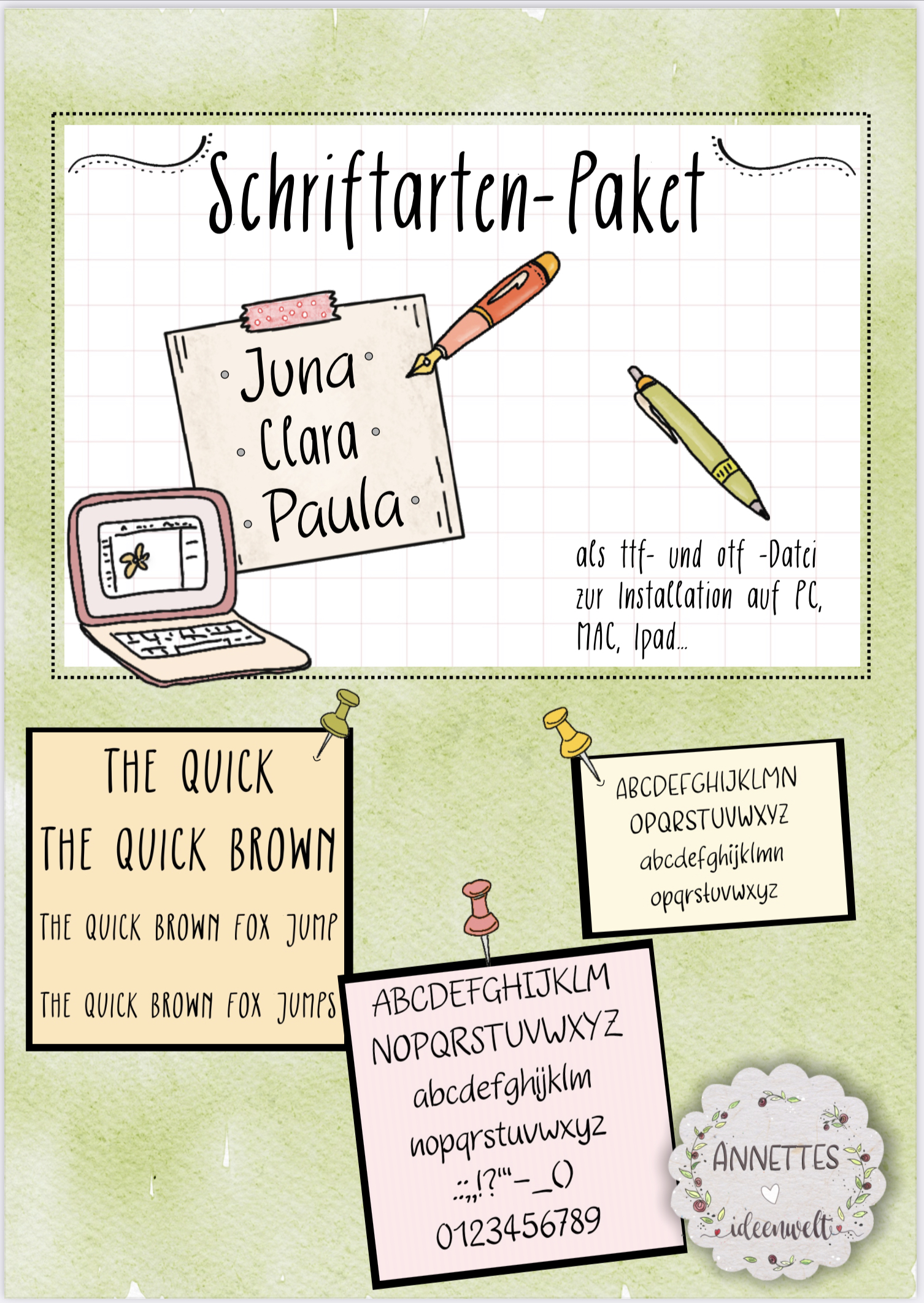
Drei klare, schlichte selbst erstellte Schriftarten, die sich hervorragend eignen um Arbeitsblätter oder sonstiges Material für die Schule herzustellen.
Schriftarten / Font Paket
Schriftart / Font "Clara"
Klare und schlichte Schriftart zum Erstellen von Arbeitsblättern und anderem Unterrichtsmaterial.Die Schriftart kann einfach installiert und in unterschiedlichen Programmen und Apps ( Windows/MAC/Ipad...) genutzt werden.
Schriftart / Font "Juna"
Klare und schlichte Schriftart zum Erstellen von Arbeitsblättern und anderem Unterrichtsmaterial.Die Schriftart kann einfach installiert und in unterschiedlichen Programmen und Apps ( Windows/MAC/Ipad...) genutzt werden.
Schriftart / Font "Paula"
Schlichte, klare Schriftart, die sich gut eignet, um Arbeitsblätter und sonstiges Material herzustellen.Die Schrift kann einfach installiert und dann in verschiedenen Programmen und Apps genutzt werden.